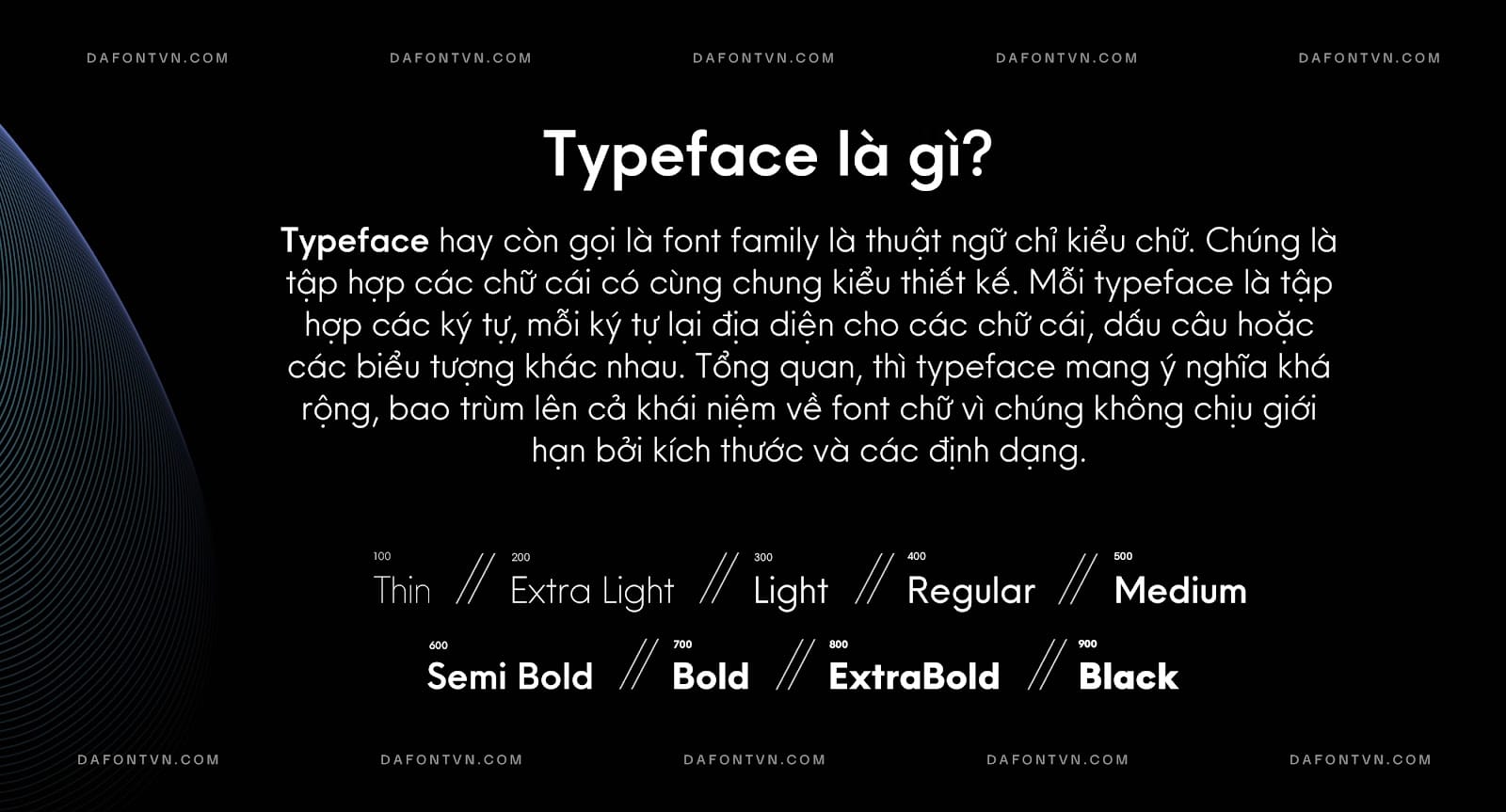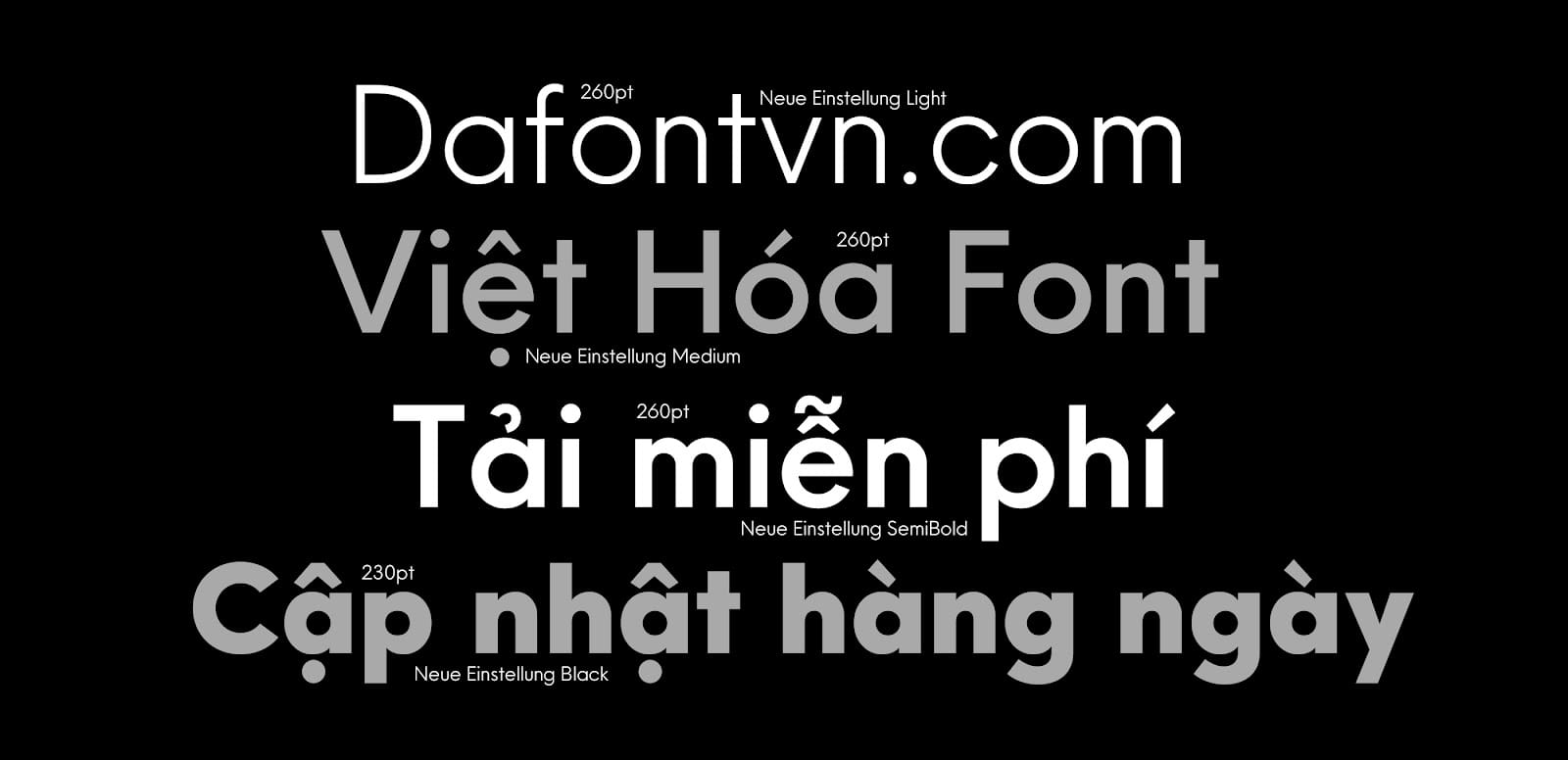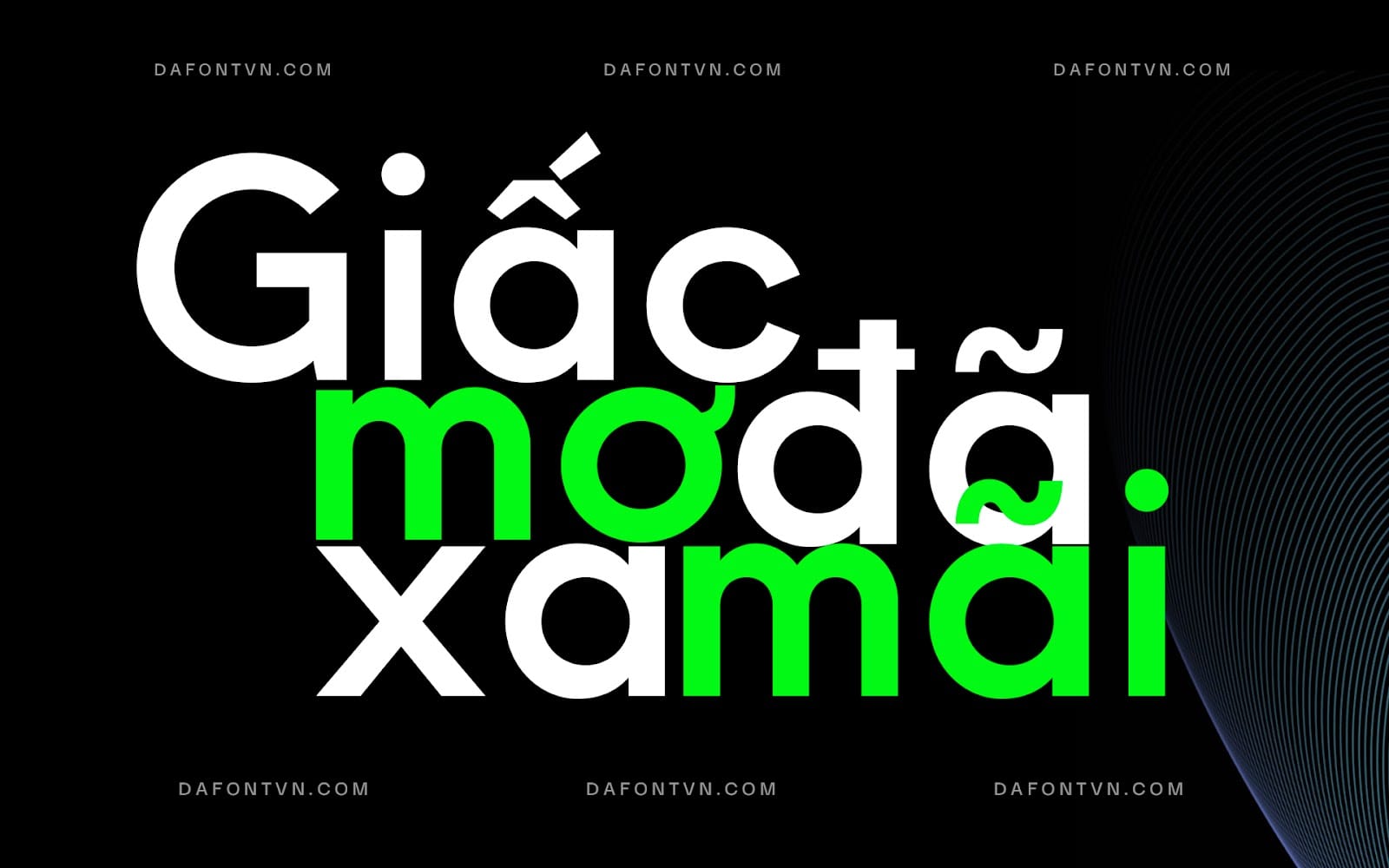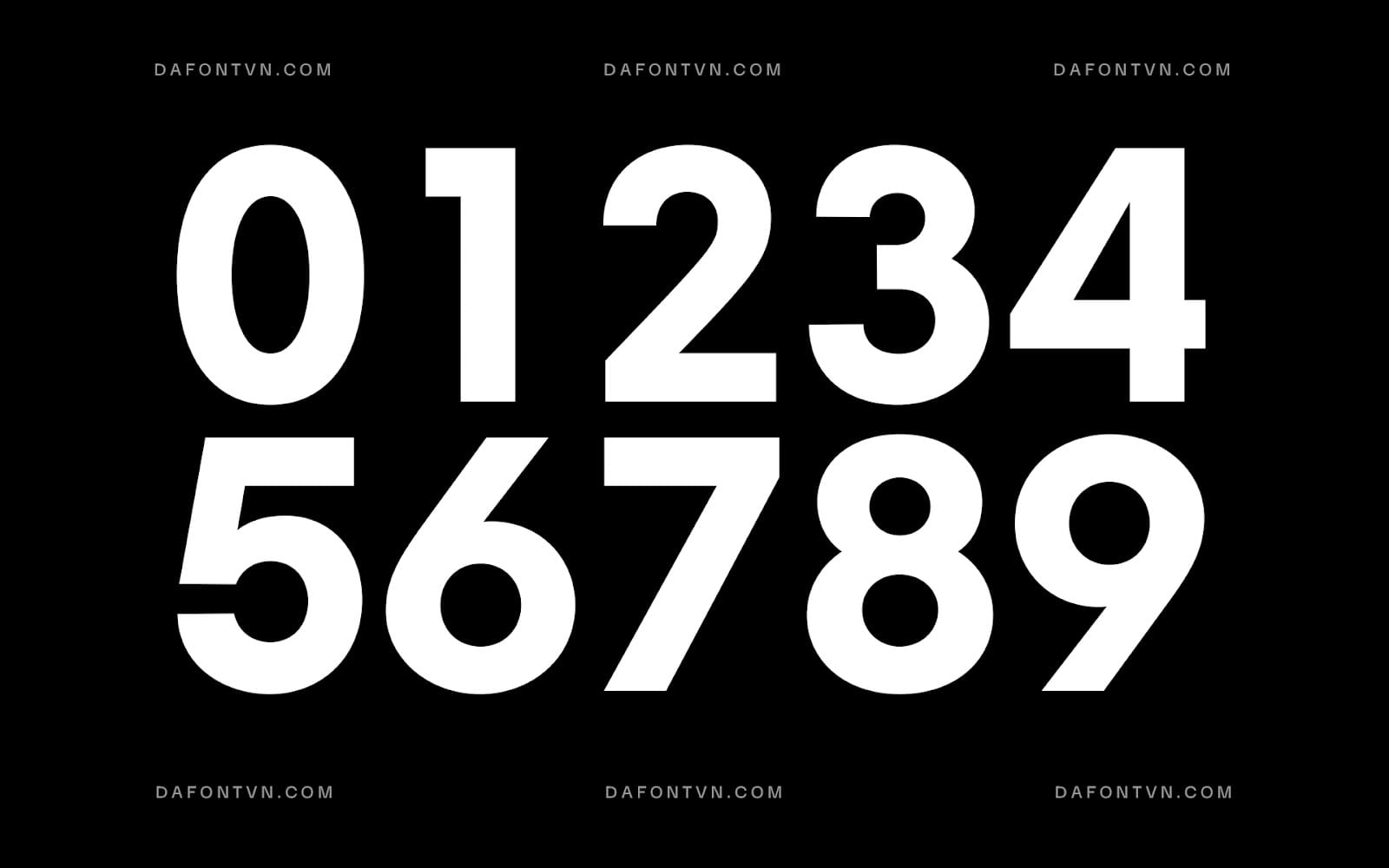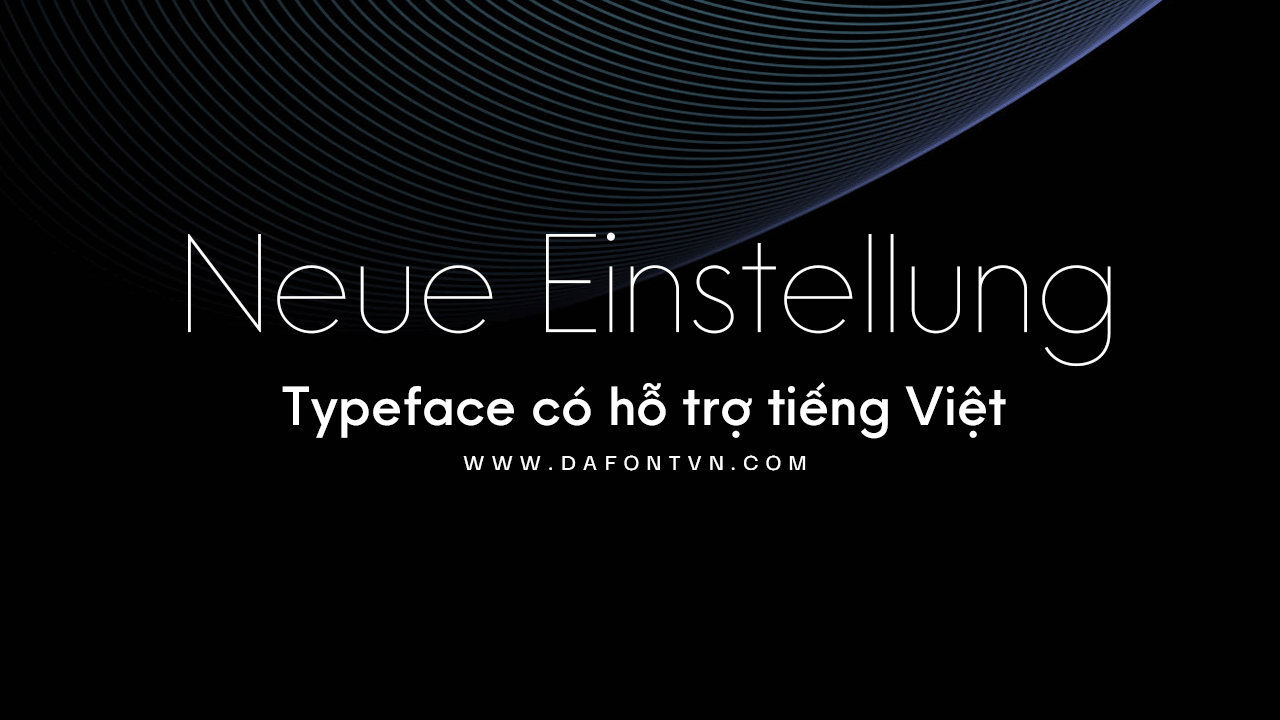
Neue Einstellung là một typeface geometric với sự đơn giản và dễ đọc. Lấy cảm hứng từ hiệu ứng Einstellung, nó thể hiện sự cứng cáp trong hình thức và mềm mại trong cách thức hoạt động. Với sự tối giản mà nó mang lại vì vậy font rất sử dụng cho hầu hết các dự án.Neue Einstellung bao gồm 9 kiểu từ Thin đến Black, tuy nhiên nó không có kiểu Italic, đặc biệt bộ font này có hỗ trợ Tiếng Việt. Neue Einstellung phù hợp cho nhiều dự án khác nhau, có thể sử dụng cho tiêu đề, logo, văn bản, website, tạp chí…